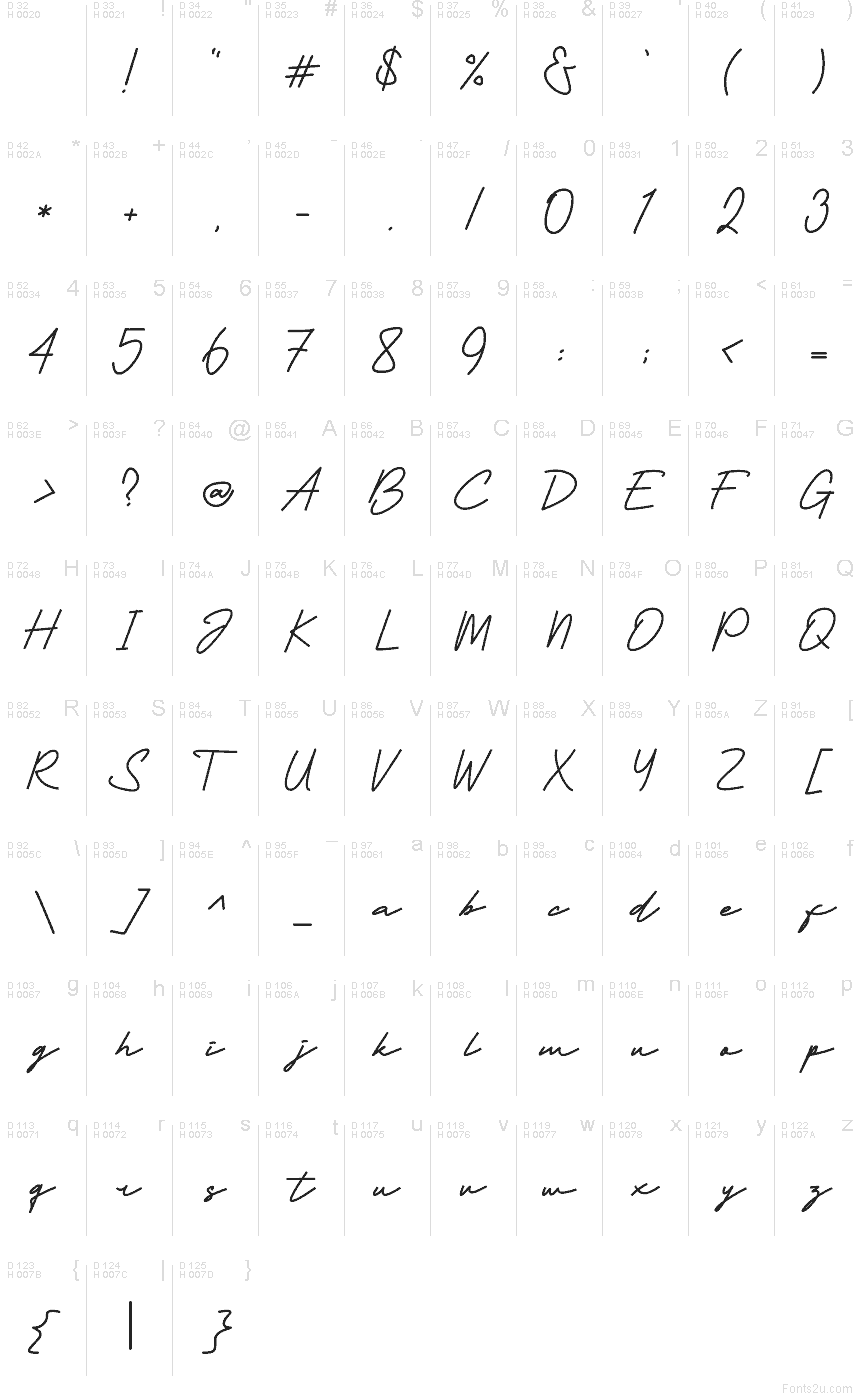
Farah Shanum Script
Farah Shanum Script od Farah Shanum z MENK Studio je bezplatné písmo pripomínajúce rýchly rukou písaný podpis. Vďaka dlhým, plynulým ťahom a ľahkému, otvorenému rytmu pôsobí pohyb písmen prirodzene a osobito, a nie len dekoratívne. Dodáva tak písmu ležérnu eleganciu, ktorá vychádza z dynamiky a gesta.
Je to prirodzená voľba pre logá, butikové balenia, nadpisy na sociálnych sieťach, pozvánky a beauty branding, kde podepsaný vzhľad pomáha nastaviť správny tón. Najlepšie vynikne v krátkych frázach a jednoslovných názvoch, pretože rozmáchly pohyb dodáva textu sebavedomú tvár bez toho, aby pôsobil príliš formálne alebo strojene.